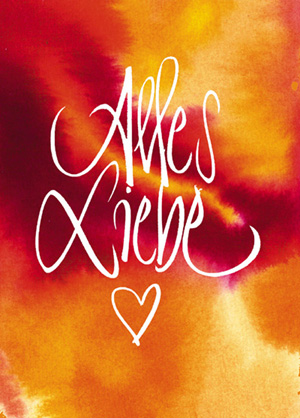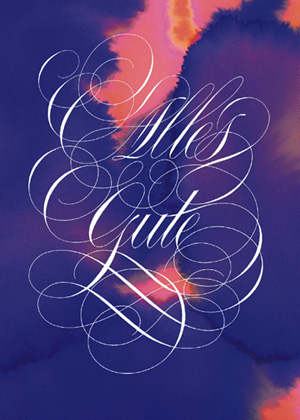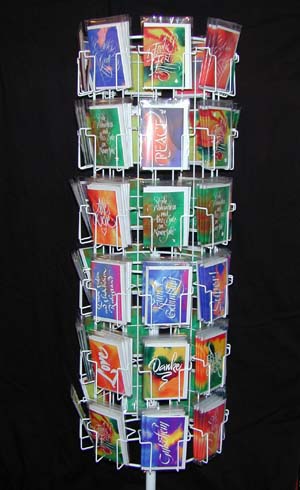
Hier sehen
Sie etwas, das Sie sicher erstaunt! Eine kalligrafische Kartenserie,
die Sie
vorher noch nie gesehen haben und die in dieser Form
zum ersten
Mal weltweit publiziert wird - gestaltet von Jean
Larcher und Katharina Pieper.
Kreation
und vierfarbiger traditioneller Offset-Druck sind von exzellenter Qualität.
extremely surprised
and
excited to see a new serie of cards which you have never seen before.
They
are imagined and published for the first time worldwide.
These
cards designed by Jean Larcher and Katharina Pieper of high quality
four
colour offset process printing have just came out!
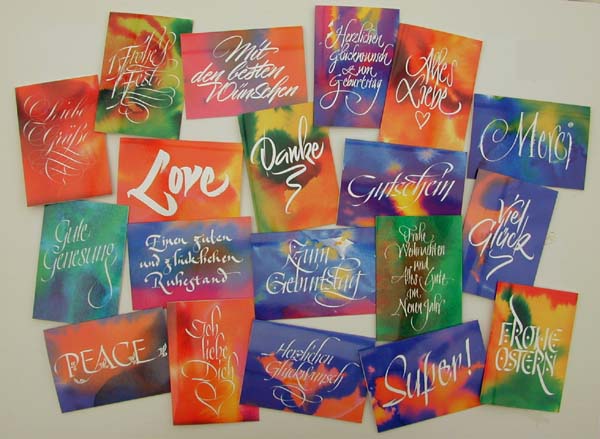
Das
Set enthält 20 glanzkaschierte Glückwunschkarten (Klappkarten) im
Format 10,5 x 14,8 cm,
ist
vierfarbig, mit Aquarellhintergründen versehen und in verschiedenen kalligrafischen
Stilen geschrieben.
Die
Karten werden mit Briefumschlägen in einer Plastik-Geschenkbox geliefert.
The
set contains 20 folded glossy cards 10.5 x 14.8 cm in full-colour. The background
is painted in watercolours
and
calligraphed in different styles. The cards will be delivered with their envelopes
in a plastic box.